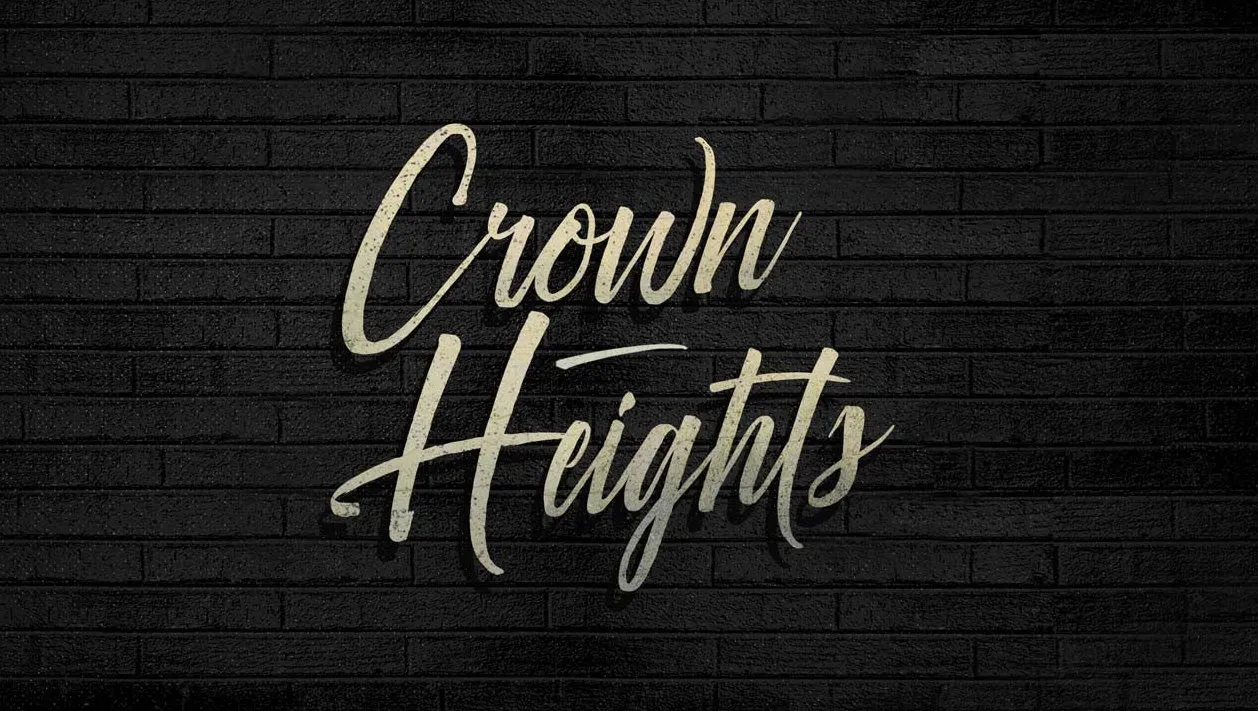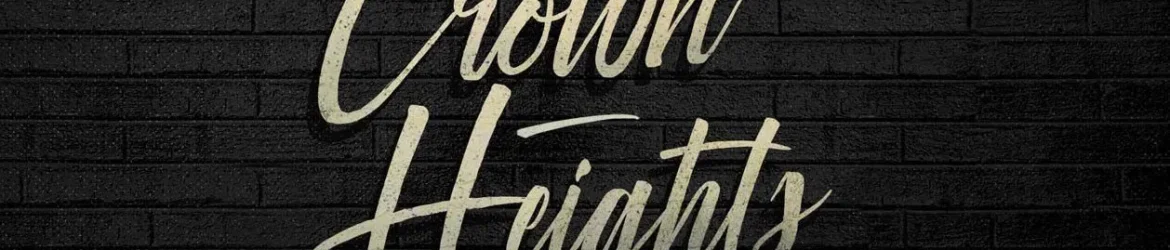
Descubra a elegância do estilo Crown Heights Script Font. Desenhado por Hamilton como uma fonte script, este elemento de texto traz um toque natural e quase desbragado com detalhes criados à mão. Seu caráter é robusto e forte, combinando elementos de design cuidadosamente para que fiquem aparentes em qualquer aplicação, seja ele na moda, no varejo online, nos blogs sobre tendências ou em qualquer negócio que deseje ser elegante e sofisticado. Ideal para adicionar um toque único à sua marca, o Crown Heights Script Font é uma escolha perfeita. Descubra como ela pode dar aos seus materiais de marketing a cara que você deseja.